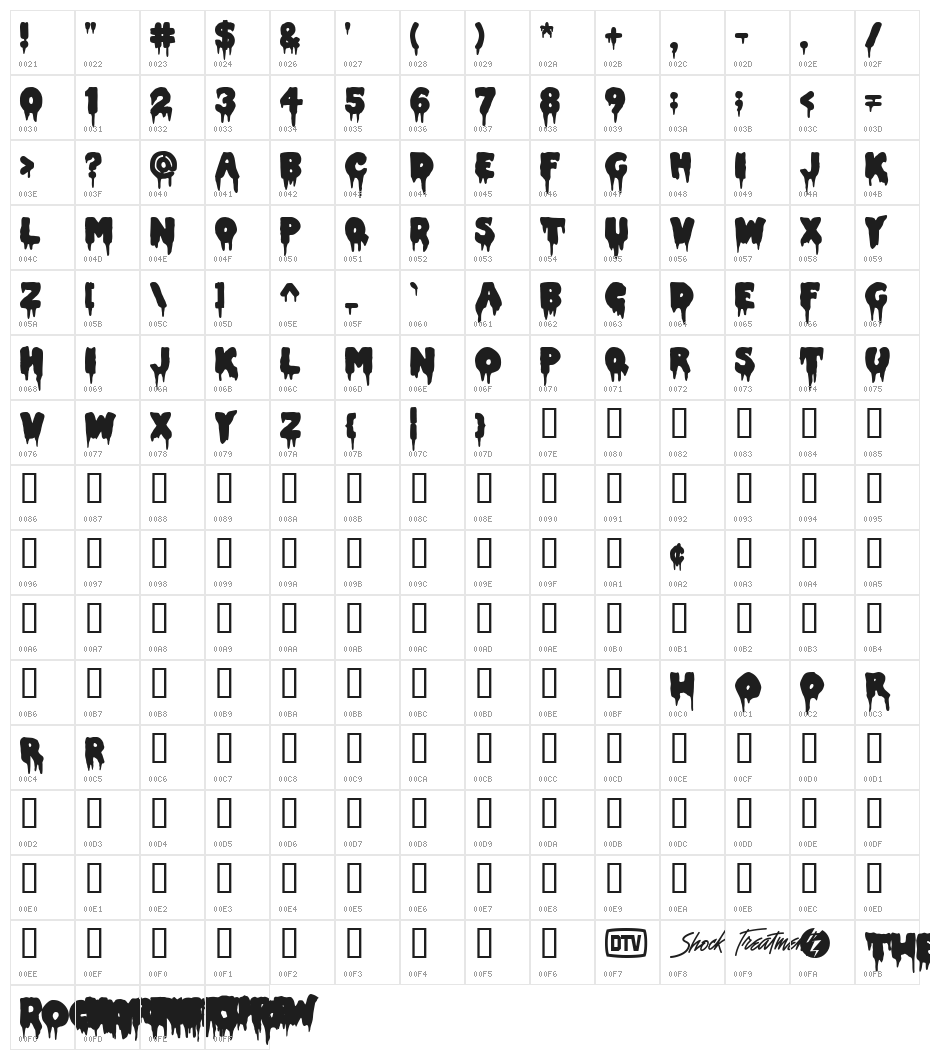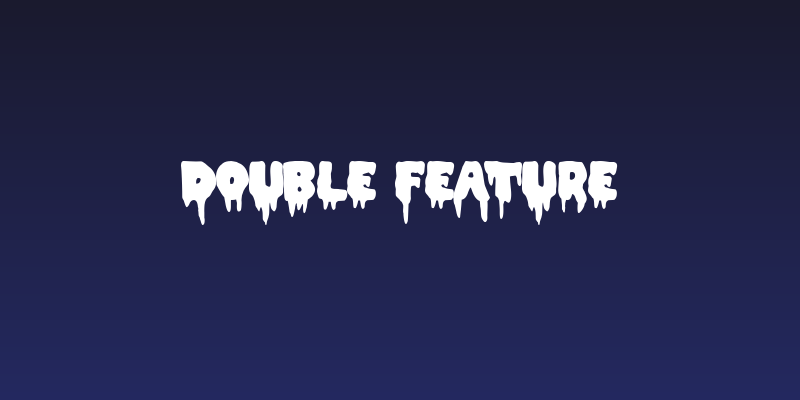
Double Feature Font
| 推荐项目 | Ideal for Halloween posters, horror movie titles, themed party invitations, or any project requiring a spooky, dramatic effect. |